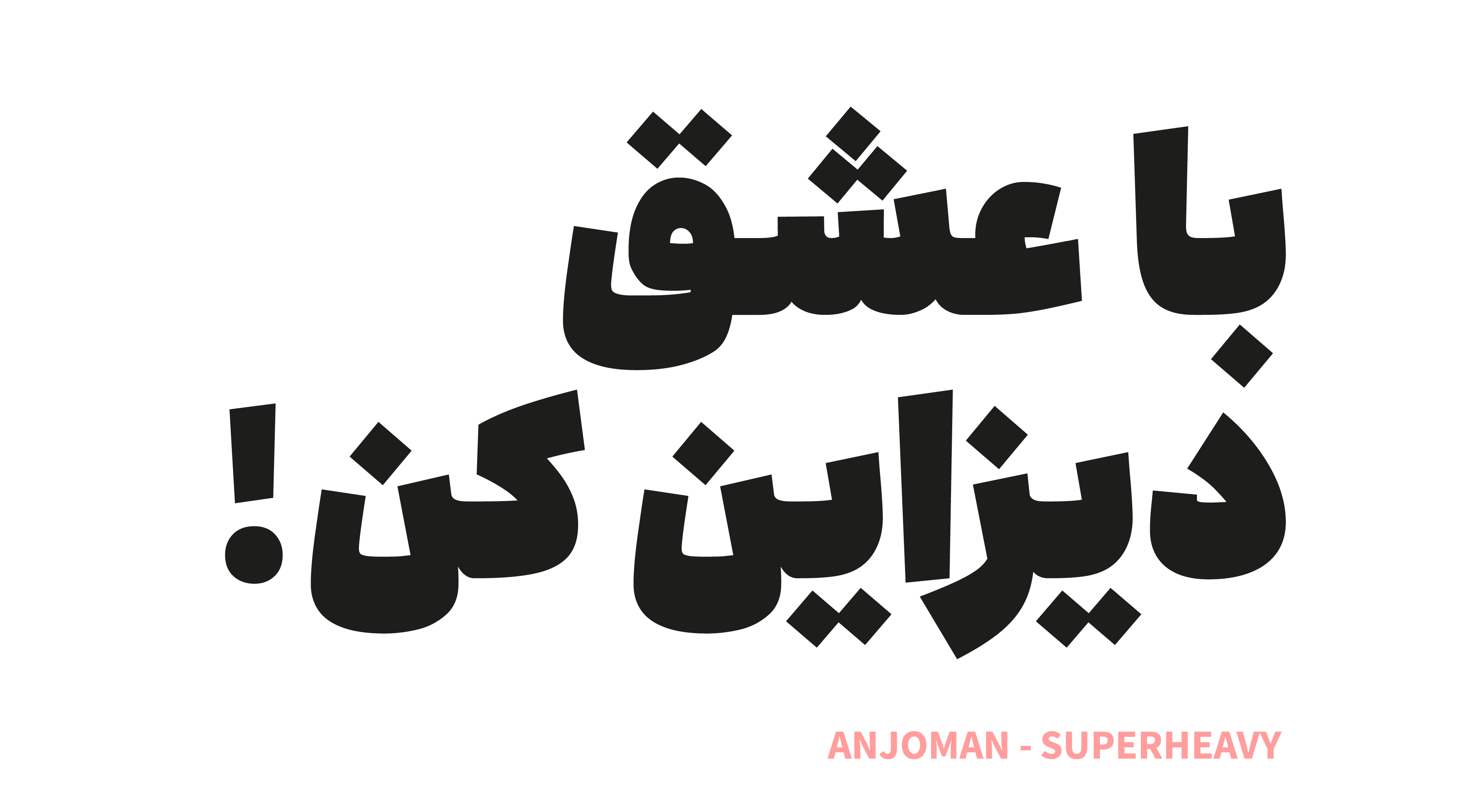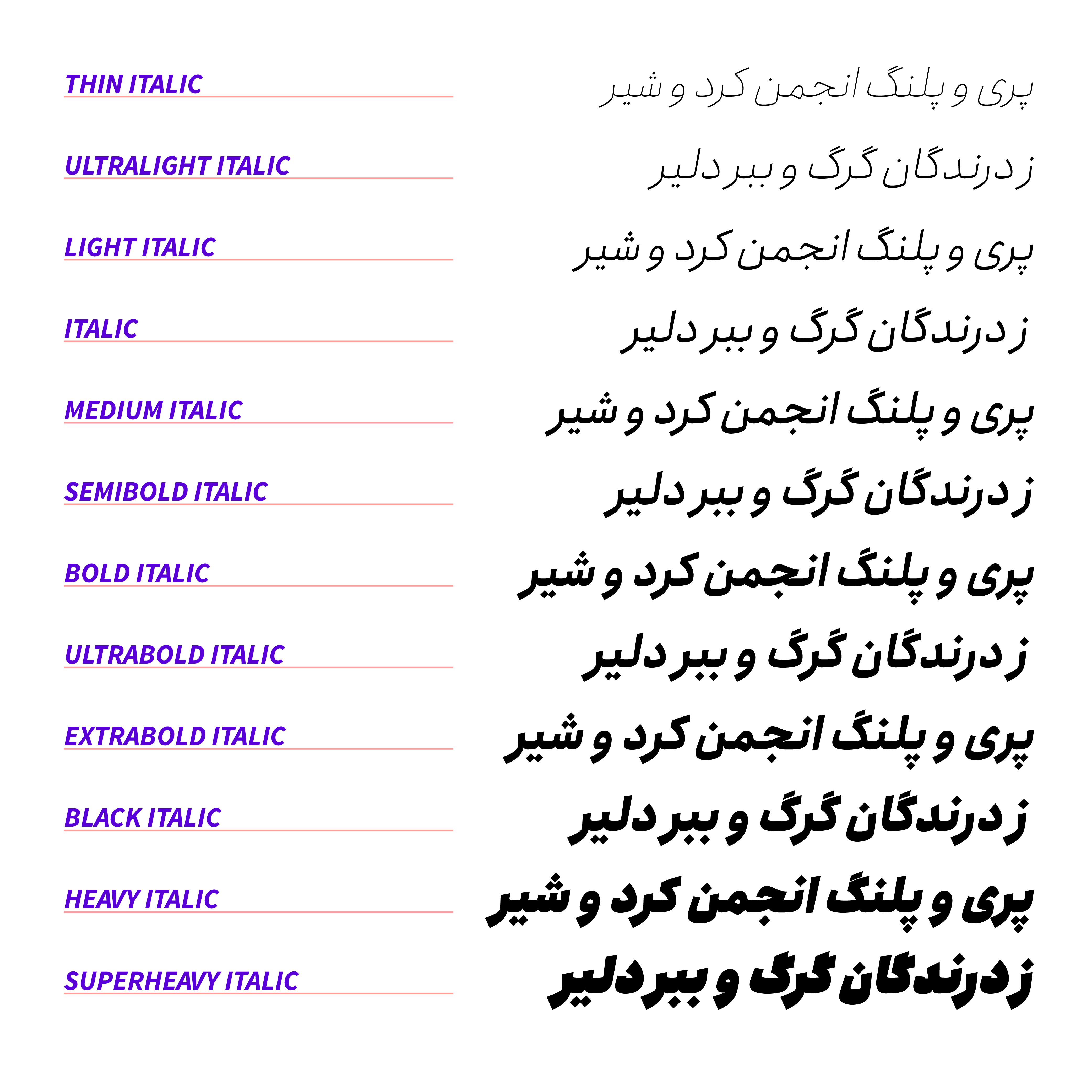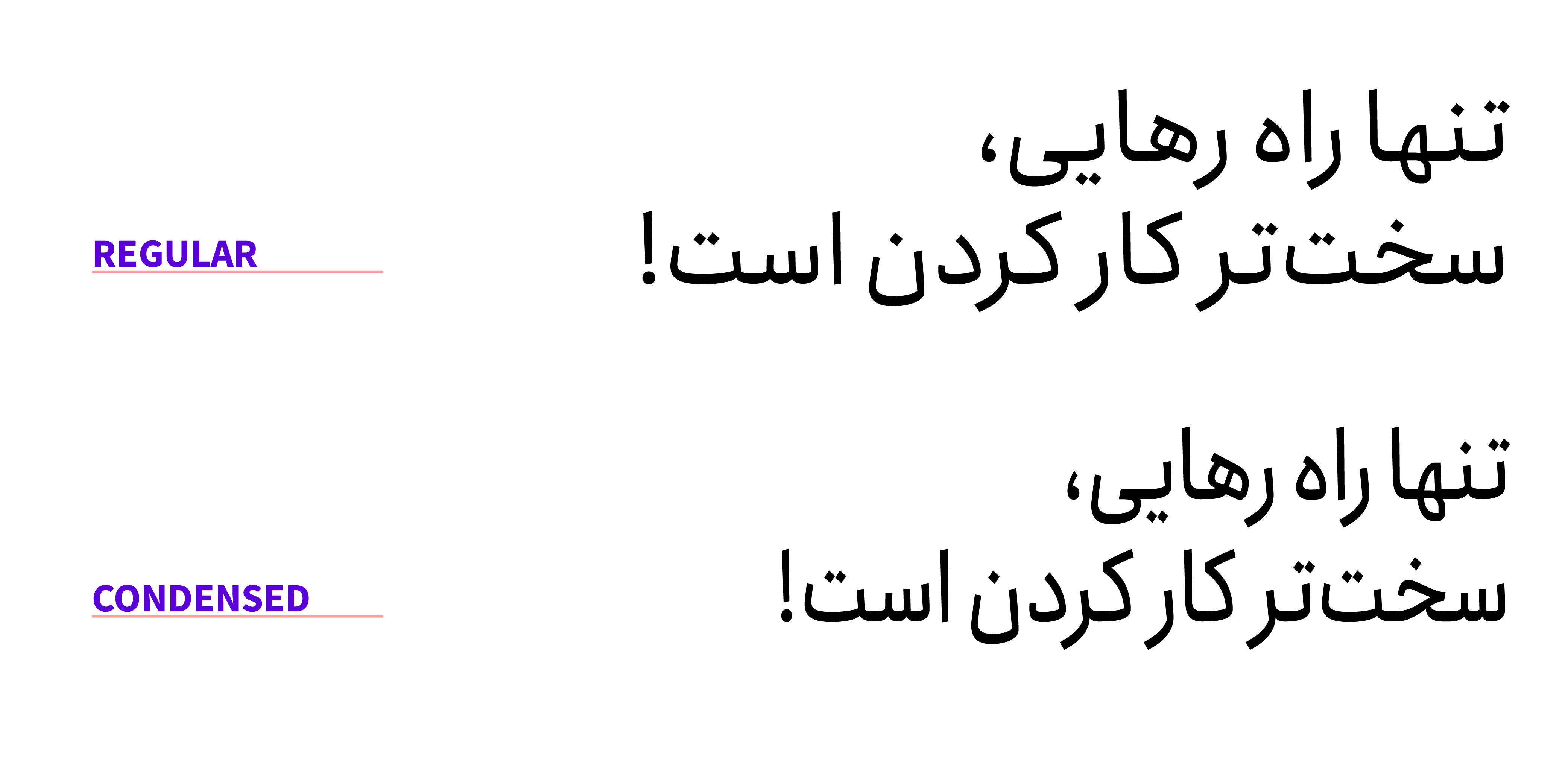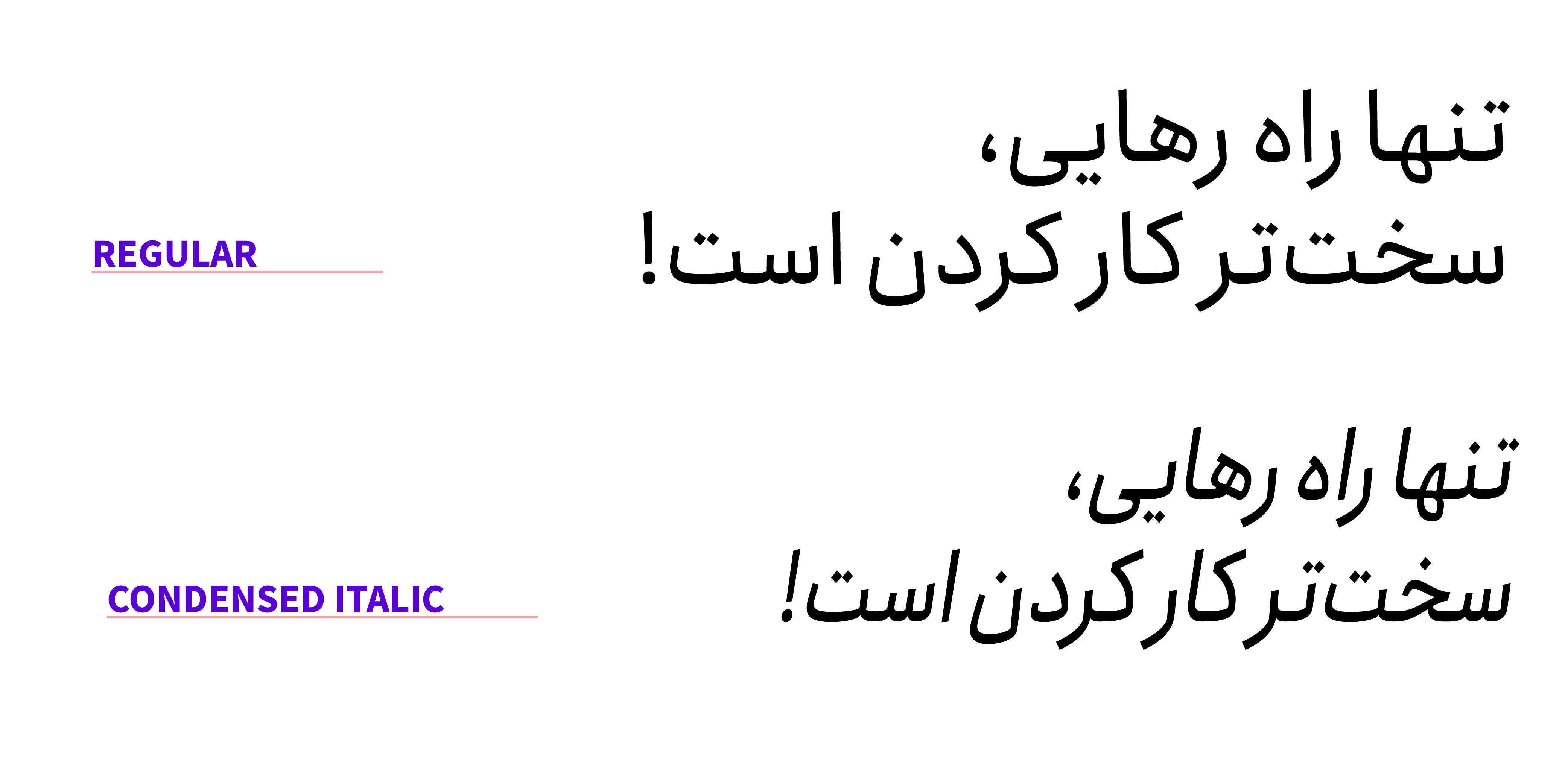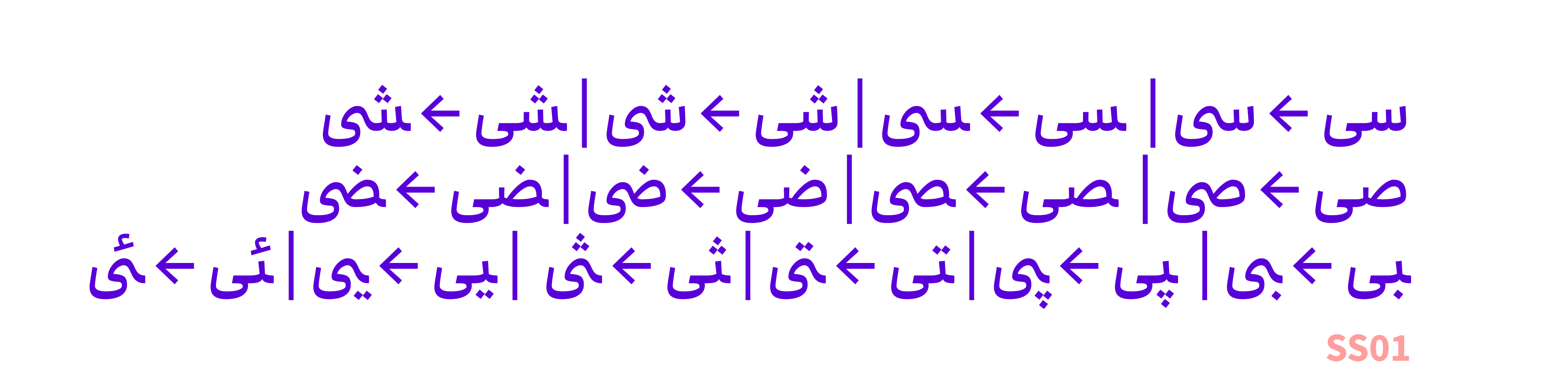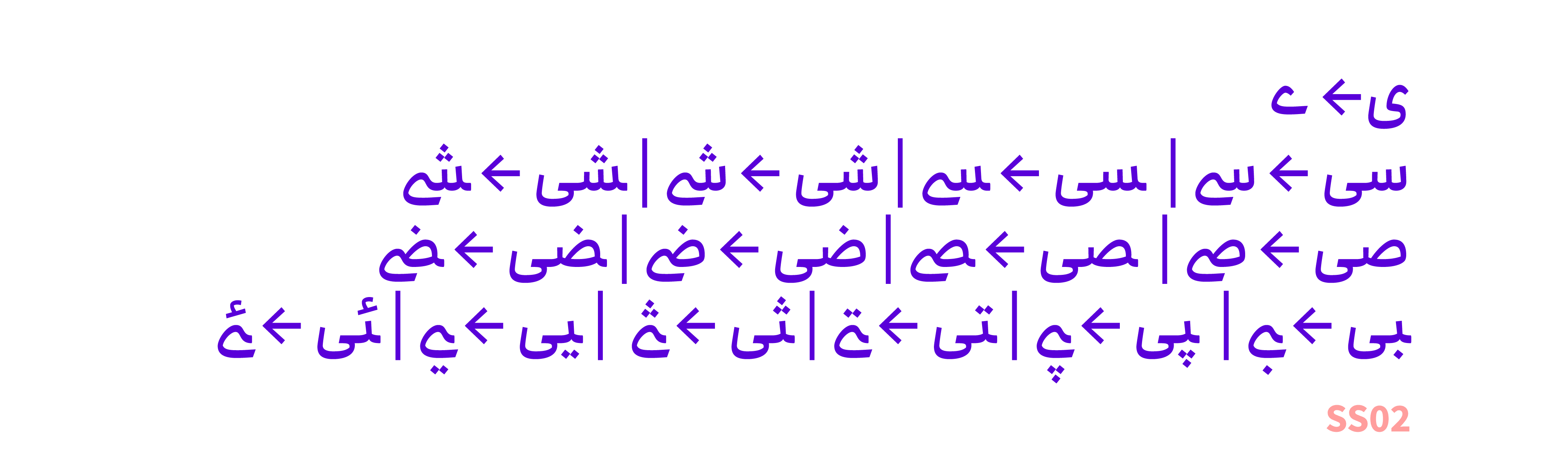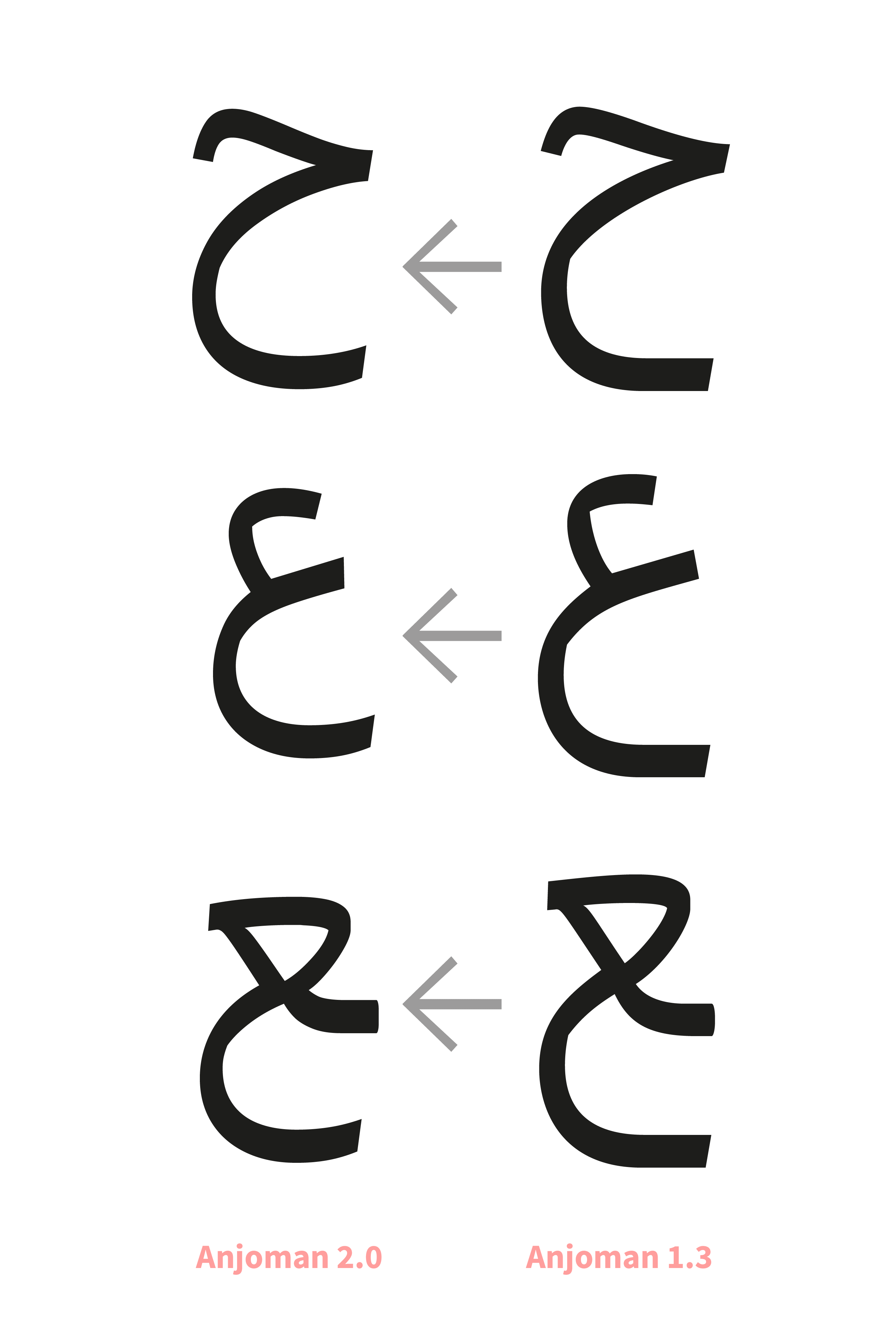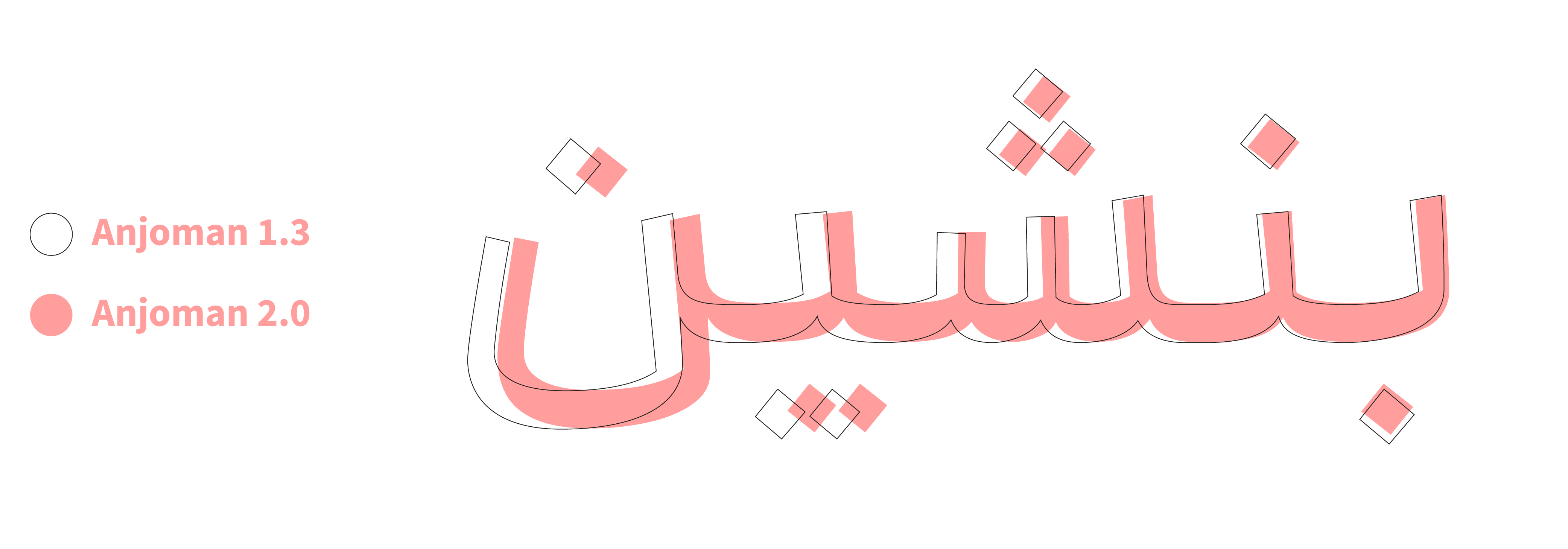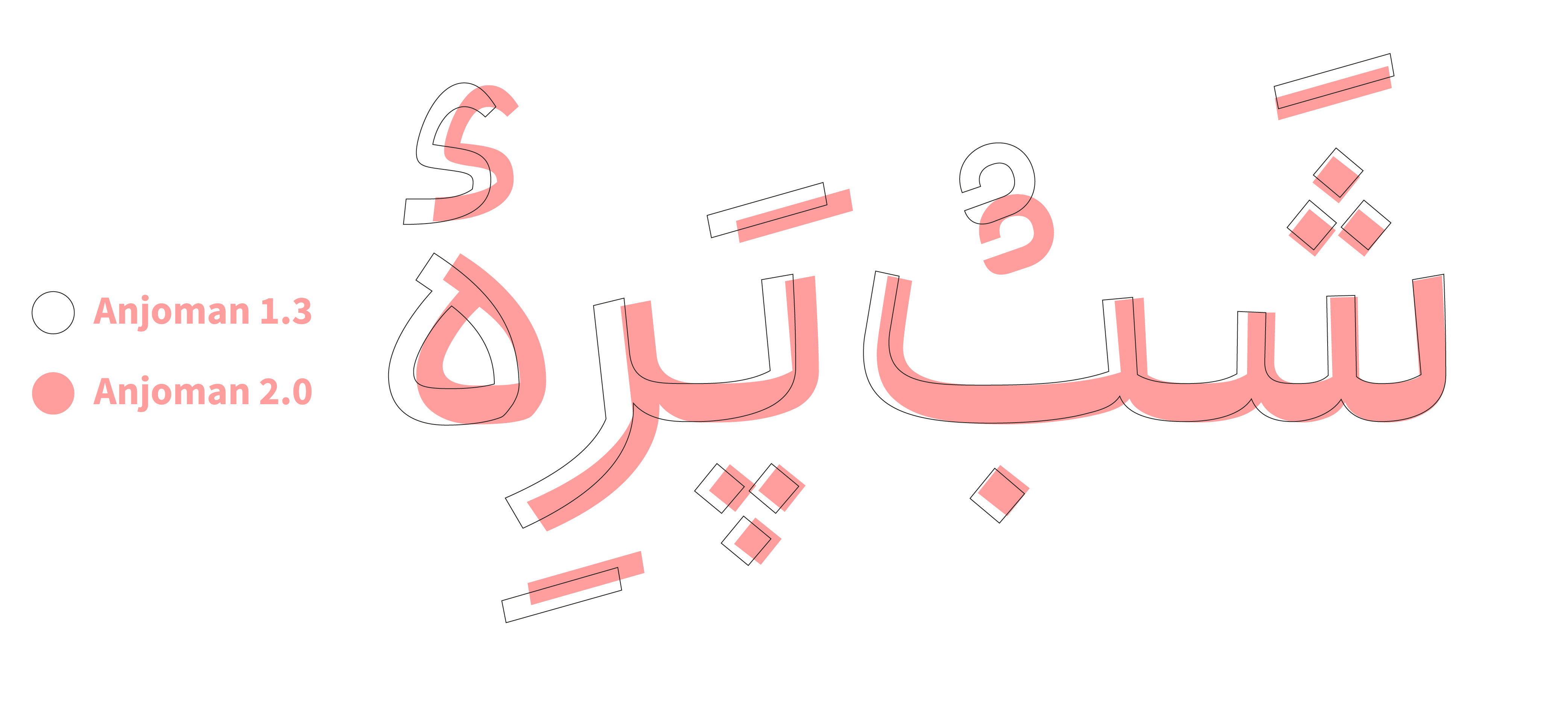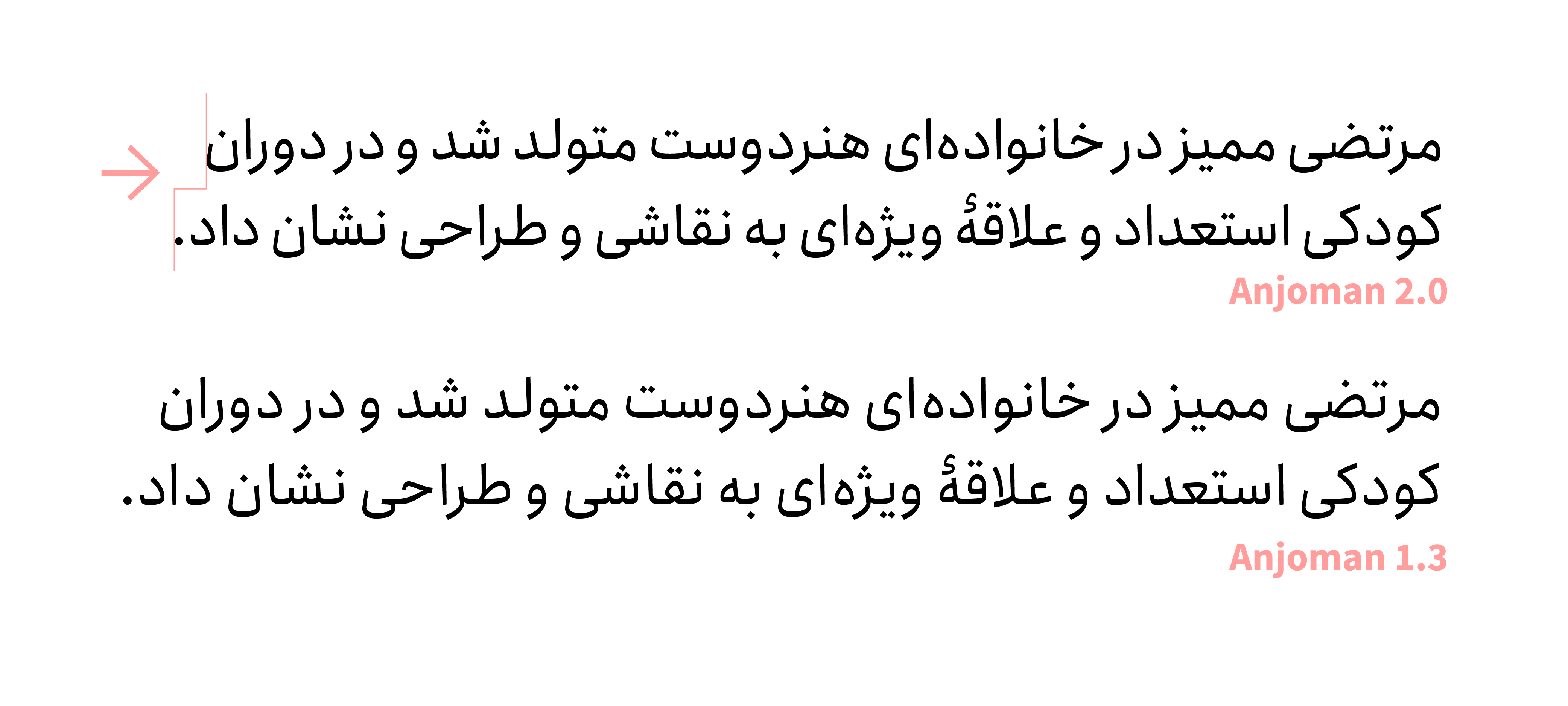
در نسخه ۲٫۰ فونت انجمن چه تغییرات و نوآوری‌هایی وجود دارد؟
در نسخه‌ی دوم خانواده حروف انجمن شاهد قابلیت‌های جدید و بهبودهای فراوانی خواهید بود که از مهم‌ترین آن‌ها می‌توان به موارد زیر اشاره کرد:
۱- وریبل فونت (Variable Font)
فونت متغیر انجمن دارای سه متغیر وزن، مایل و فشرده است. این متغیرها در وب و نرم‌افزارهایی که از وریبل فونت فارسی پشتیبانی می‌کنند قابل استفاده است. این ویژگی در بسته تمام حرفه‌ای در اختیار شماست.
متغیر وزن:
متغیر مایل:
متغیر فشرده:
۲- وزن جدید SuperHeavy
یک وزن جدید بسیار سنگین در نسخه‌ی دوم برای خانواده فونت انجمن طراحی شده است. این وزن بسیار سنگین مناسب عنوان‌ها و فضای تبلیغات است و نباید در اندازه کوچک از آن استفاده کرد.
۳- سبک مایل (Italic)
در نسخه دوم فونت انجمن نسخه مایل طراحی و پیاده‌سازی شده است. سبک مایل در انجمن با خم شدن حروف به سمت راست ساخته شده است که علاوه بر استدلال علمی و تاریخی، با جهت خم شدن حروف در زبان‌ انگلیسی هم‌آهنگ است و ایجاد اغتشاش نمی‌کند.
۴- سبک فشرده (Condensed)
برای تایپوگرافی حرفه‌ای در وب و چاپ، لازم است تا بدون آسیب دیدن حروف و تناسبات آن، نوشته در فضای معین و محدودی جانمایی شود. سبک فشرده در فونت انجمن این ویژگی را برای شما به همراه دارد.
۵- سبک فشرده مایل (Condensed Italic)
از ترکیب دو حالت فشرده و مایل، سبک فشرده-مایل بوجود آمده است تا همچنان دیزاینرها با آزادی عمل بیشتری اقدام به چینش متن‌ها کنند.
۶- سبک‌های جایگزین ترکیبات و حروف (Stylistic Sets)
برای توانایی بیشتر دیزاینرها در تایپوگرافی و ایجاد ترکیب‌های مناسب در متن‌ها، نسخه دوم انجمن ترکیب‌های فراوانی از حروف را در اختیار می‌گذارد که در نرم‌افزارهای مختلف می‌توان به صورت جداگانه و یا هم‌زمان آن‌ها را فعال کرد. این امکان در بخش Stylistic Sets در دسترس است.
۷- اصلاح فرم حروف
تمامی حروف در نسخه دوم انجمن مورد بازبینی و اصلاح قرار گرفته اند تا حروفی یکدست‌تر داشته باشیم. ملموس‌ترین این بهبودها در خانواده ر، ع،ح، ک و گ است.
۸- اصلاح جانمایی نقطه‌ها
جانمایی نقطه‌ها در راستای ایجاد هماهنگی بیشتر در تمامی حروف و وزن‌ها بهبود پیدا کرده است.
۹- اصلاح جانمایی اعراب
جانمایی اعراب در راستای ایجاد هماهنگی بیشتر در تمامی حروف و وزن‌ها بهبود پیدا کرده است.
۱۰- اصلاح فاصله گذاری
یکی از مهم‌ترین عوامل یکدست دیده شدن متن، فاصله‌گذاری درست است. در نسخه دوم انجمن این فاصله‌ها با وسواس و دقت بالایی بازبینی و بهبود پیدا کرده است که در مدیریت فضا و مصرف آن تاثیر بسزایی گذاشته است.
۱۱- اصلاح فرم اعداد
ارتفاع و فرم اعداد در وزن‌های مختلف انجمن اصلاح شده است تا نتیجه مطلوب‌تری از نظر دیداری ایجاد کند.
۱۲- پشتیبانی از زبان کردی
با توجه به نیاز کاربران، کاراکترهای زبان کردی به فونت انجمن افزوده شده است تا هم‌وطنان کرد زبان هم بتوانند از انجمن استفاده کنند.